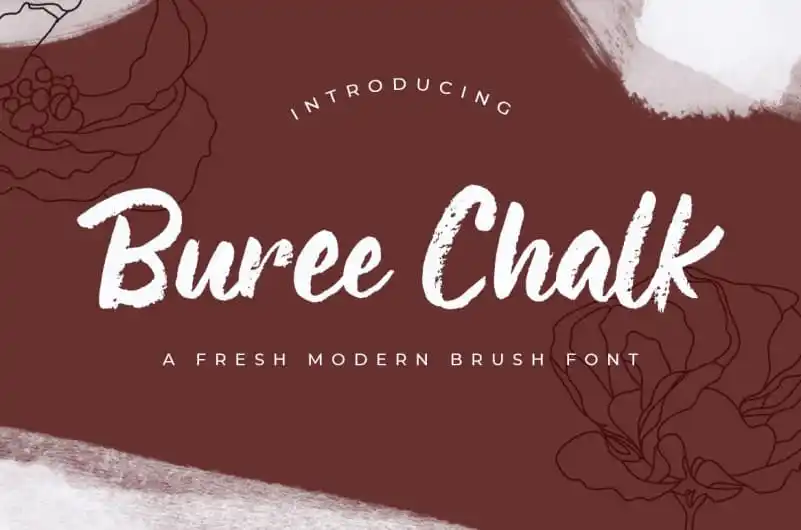
Buree Chalk Brush Font – Download Grátis
A fonte “Buree Chalk Brush” é uma elegante escolha para projetos que precisam de um toque deslavado e quase natural. Ela traz a sensação suave e úmida de um caderno de caderneta, com o formato de uma borracha em uso casual. Esta fonte é perfeitamente adaptada para aplicativos como cartazes de eventos, designs para redes sociais ou até mesmo em livros de notas pessoais. Ela traz a personalidade e a autenticidade que você precisa para seus projetos manuscritos, apresentando um estilo que combina delicadeza com uma sensação quase selvagem da natureza. Adotar esta fonte é como dar vida à sua ideia, transformá-la em algo realmente único e especial. Ela não apenas aprimora a qualidade de seu design, mas também adiciona um toque autêntico que torna seu trabalho inovador ainda mais envolvente. Com “Buree Chalk Brush Font”, você pode criar projetos manuscritos com uma aparência tão vívida e quase natural quanto se escreverem a mão em cadernos desgastados. Seja para uso personalizado ou comercial, essa fonte se assemelha a um caderno de notas perfeitamente autêntico – apenas esperando para ser usado por você.